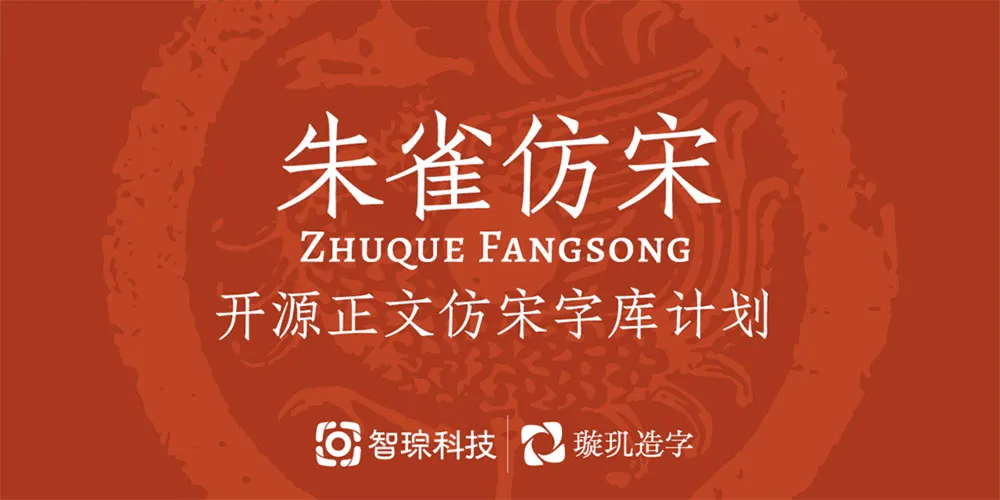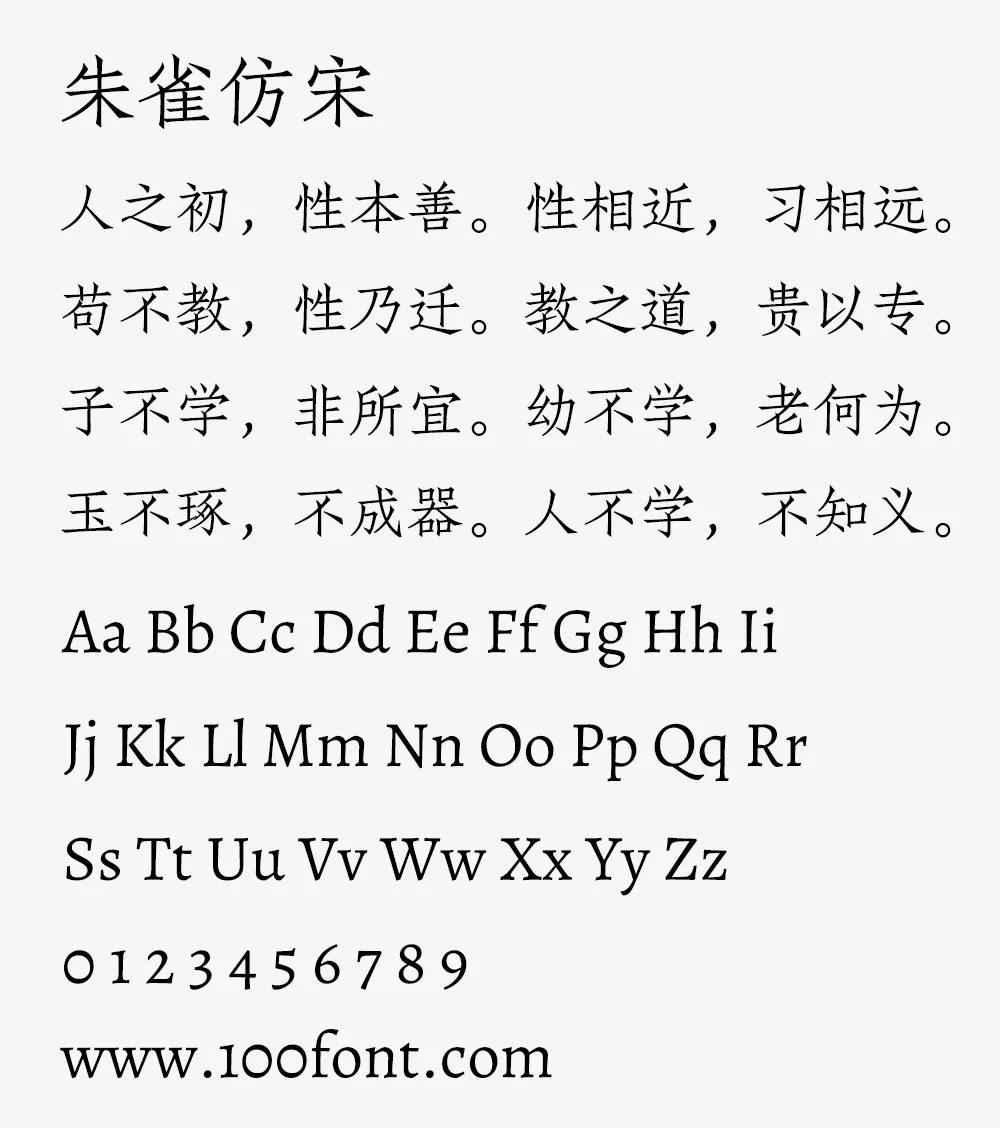
「朱雀仿宋」是璇璣造字的開源仿宋字體計劃,志在最終提供高質量的、支持多語言的正文仿宋解決方案。
仿宋作為「宋黑仿楷」中文四大基礎字體之一,長期缺乏開源許可證下的選擇。我們希望「朱雀仿宋」可以彌補這一空缺,為開源軟件與 TeX 社區貢獻一份力。
上世紀初,仿宋活字一度品類繁盛,開發、應用風行一時。然而時過境遷,市面上的仿宋最終收斂於「華豐真宋」一系,這也是今天大多數人所熟悉的仿宋樣貌。「朱雀仿宋」則以民國仿宋活字「南宋」為藍本,在滿足現代排印需求的前提下,嘗試為正文仿宋字庫帶來一縷新鮮空氣。
當前我們發佈的「朱雀仿宋」仍為「預覽測試版」,尚處於項目早期階段;無論是設計風格還是字形、排版質量,都不代表正式版情況。
璇璣正在嘗試一種全新中文字庫設計模式。得益於我們開發的最新技術,璇璣的設計師可以直接將人工智能作為設計工具去使用,我們也因此能以迭代的方式開發「朱雀」。
設計故事:智琮的智能造字技術可以讓設計師將 AI 作為設計工具去使用,可快速從拼字甚至是手寫字優化成高質量的風格字形。
開發一套開源仿宋字庫的想法最早始於 2021 年初,是繼「未來熒黑」項目之後,我們認為更有意義、也更具難度的挑戰。隨著設計研究的深入與技術進步,特別是去年以來 AIGC 技術的爆發,實現這一想法在今日遂成可能。
《足本歐陽永叔全集》,1936 年大東書局刊行。使用南宋活字排印,主創自藏。
「朱雀仿宋」改刻自民國活字「南宋」,試圖為這套沉睡數十年的字體賦予新生。「南宋」是 1932 年「百宋書局」推出的仿宋體活字,韓佑之設計原稿,鄒根培雕刻字模。一經面世,即廣泛用於書籍、期刊排印。「南宋」與大多數正文字體的設定不同的是,它中宮收緊,重心略靠右下,撇捺舒展,筆畫的粗細變化強烈,含蓄秀美而充滿力量感,在排印標題和正文時展現出濃厚的「書卷氣」。
在「南宋」活字的基礎上,「朱雀仿宋」稍稍削弱了筆畫的對比度,適當地規整了字形結構與版面效果,同時最大程度地保留了「南宋」的獨特氣質與活字趣味。
「朱雀」是中國傳統文化中「四象」之一,南方七宿之神。以「朱雀」為名,暗合了「南宋」淵源與「璇璣造字」的品牌名。